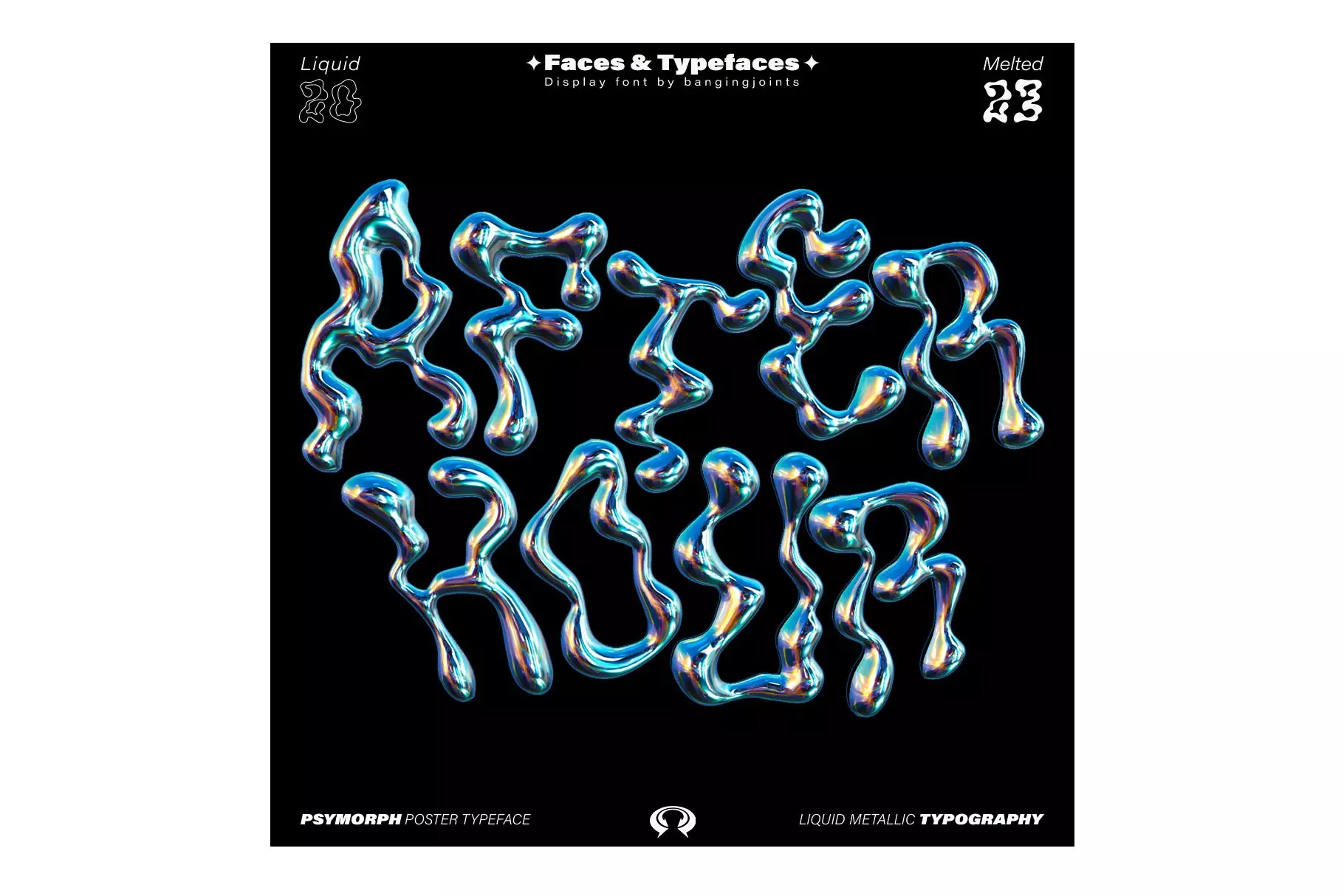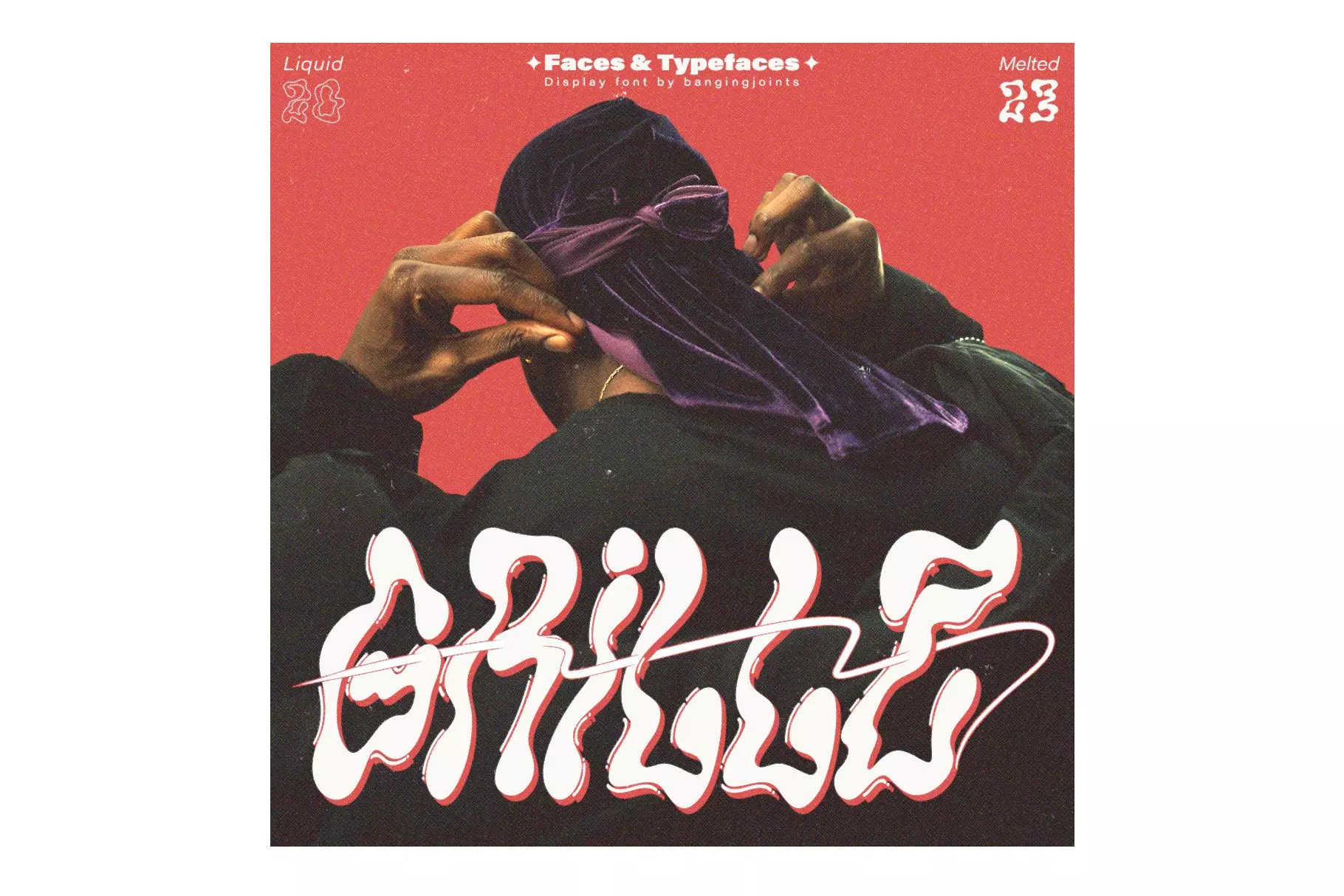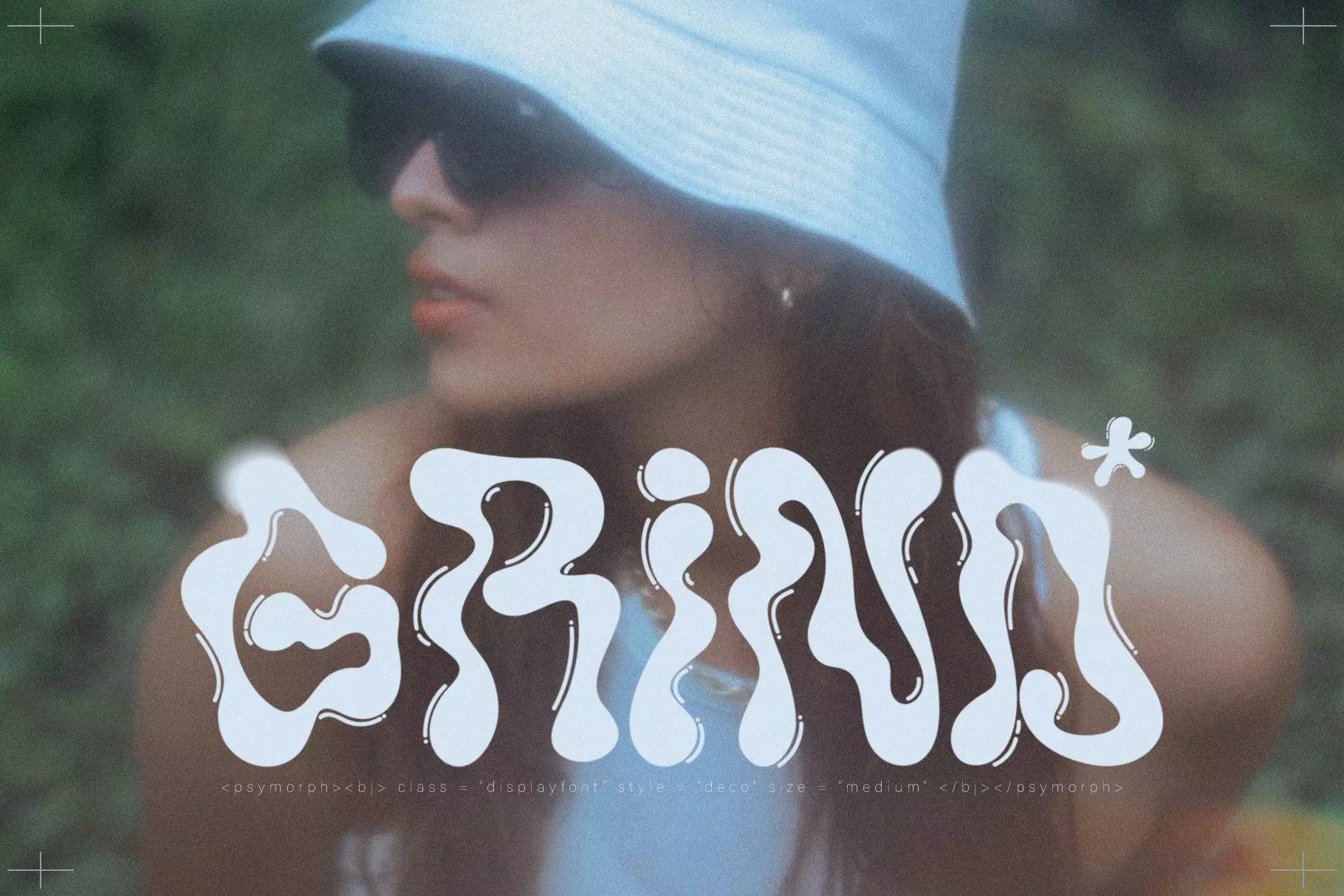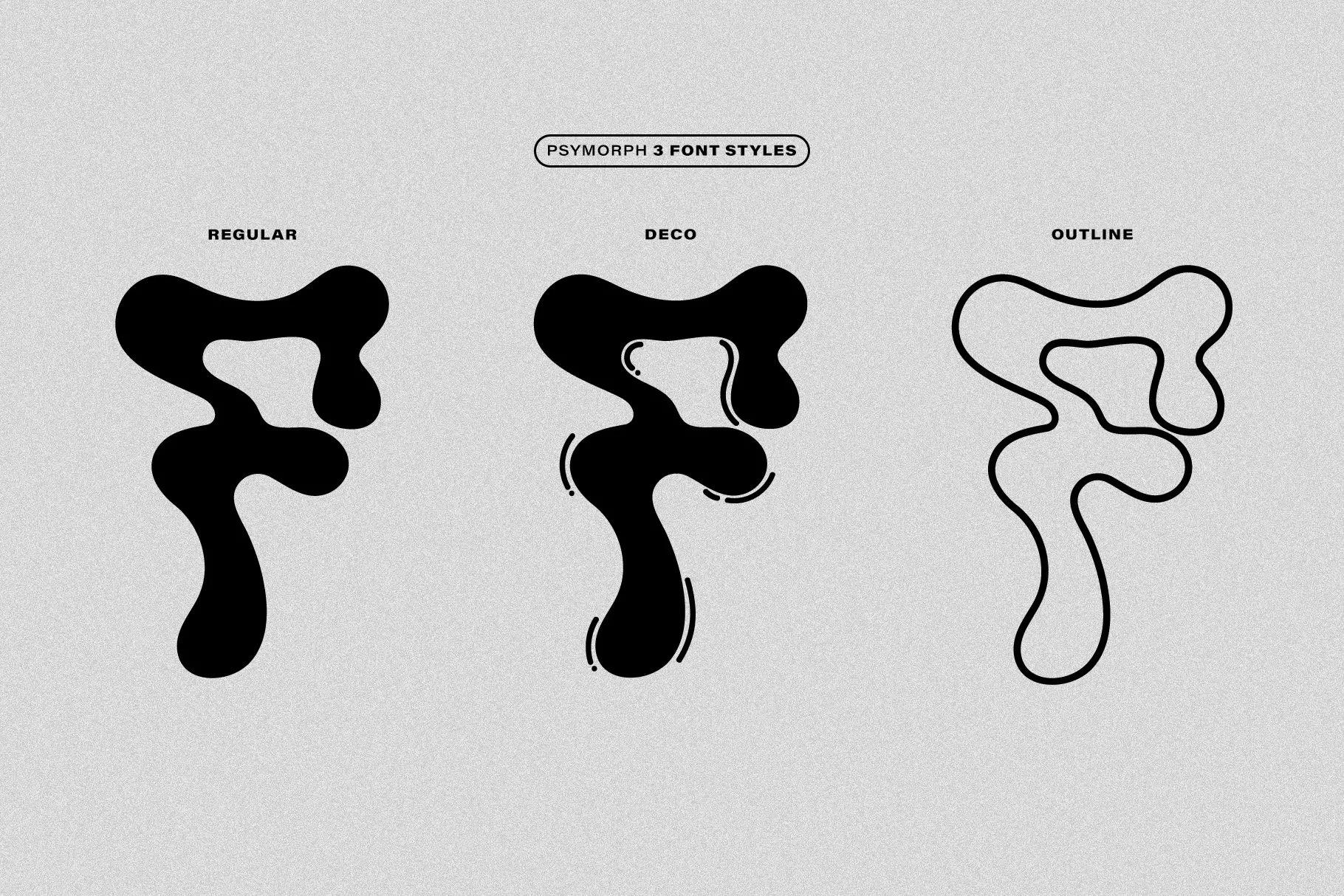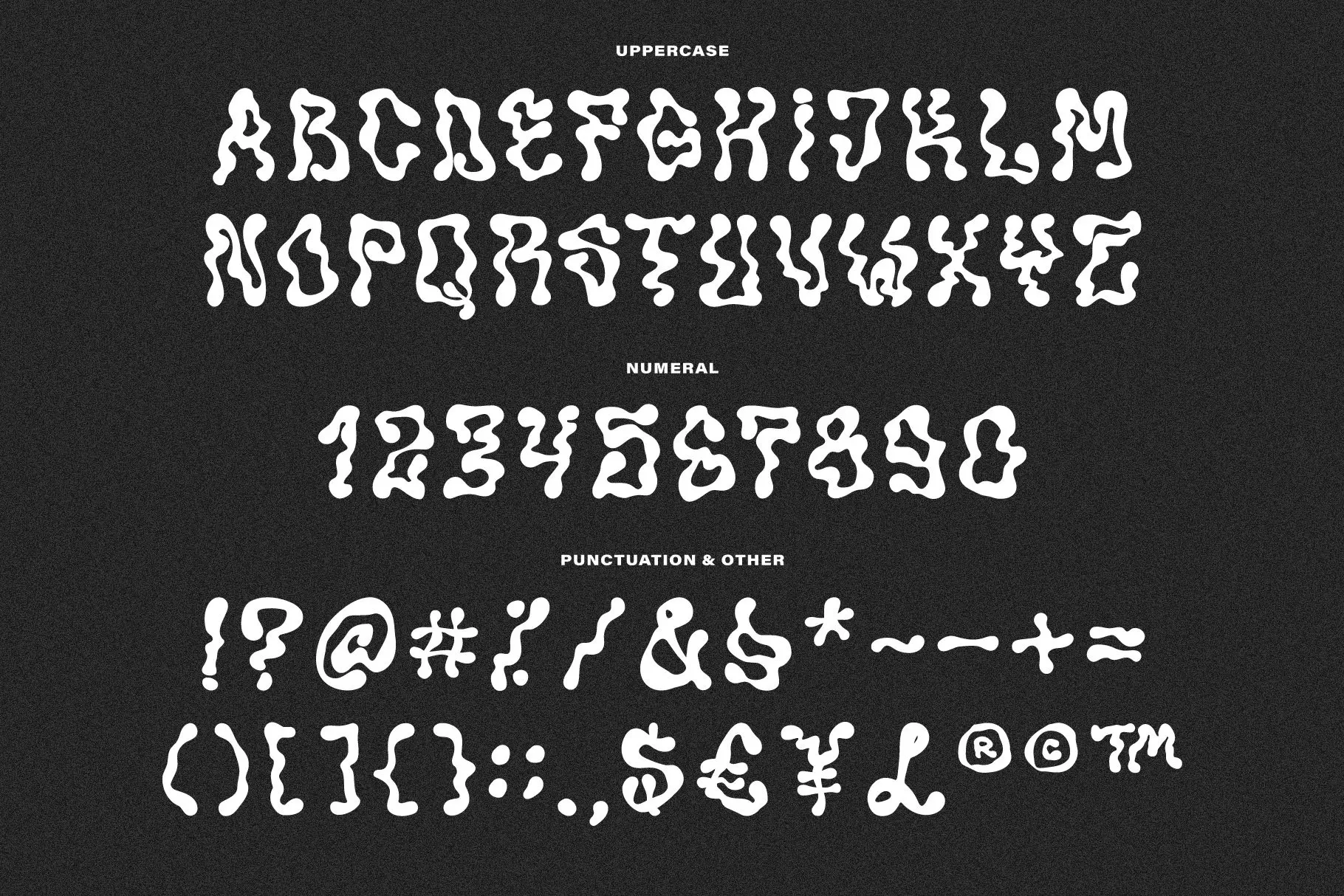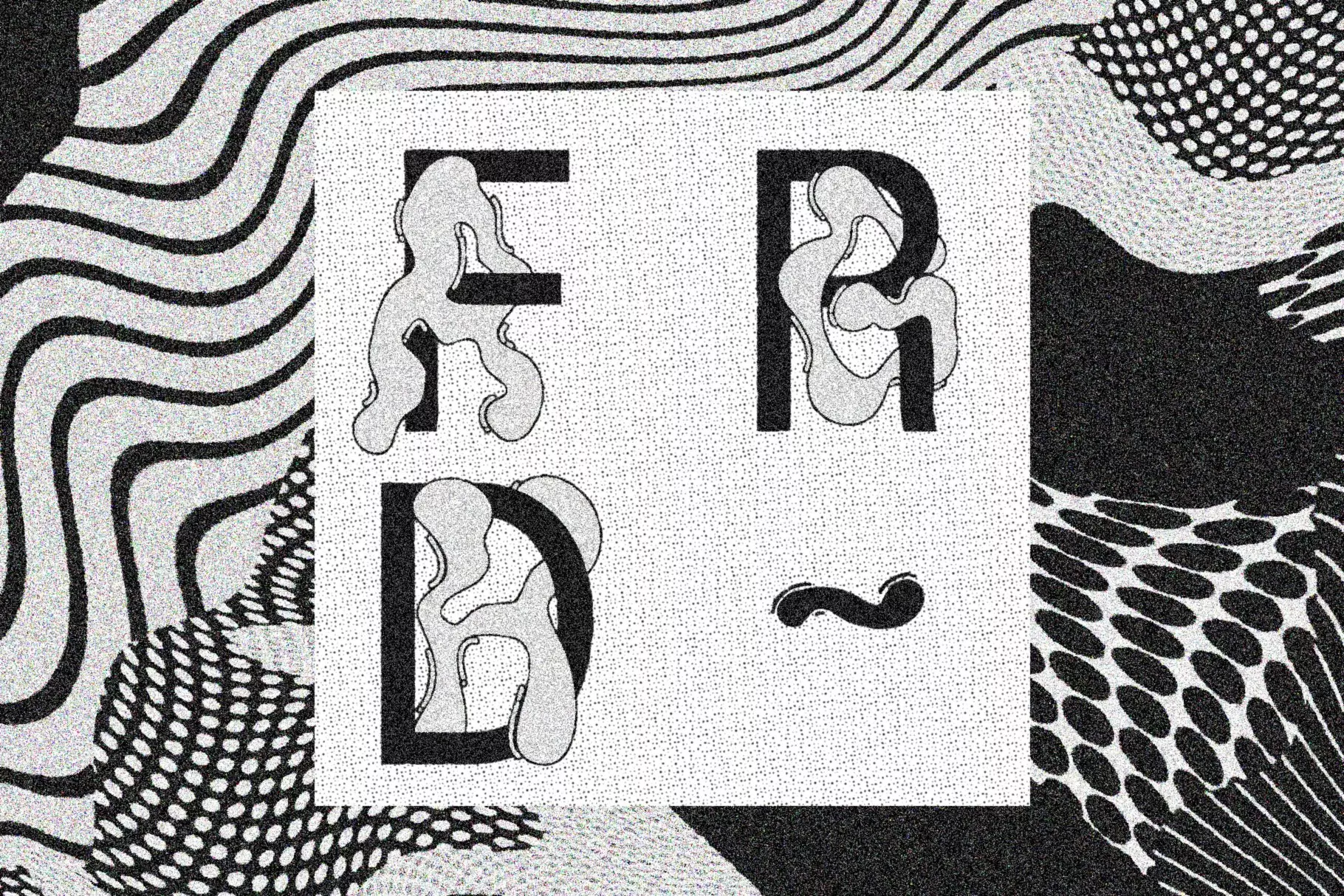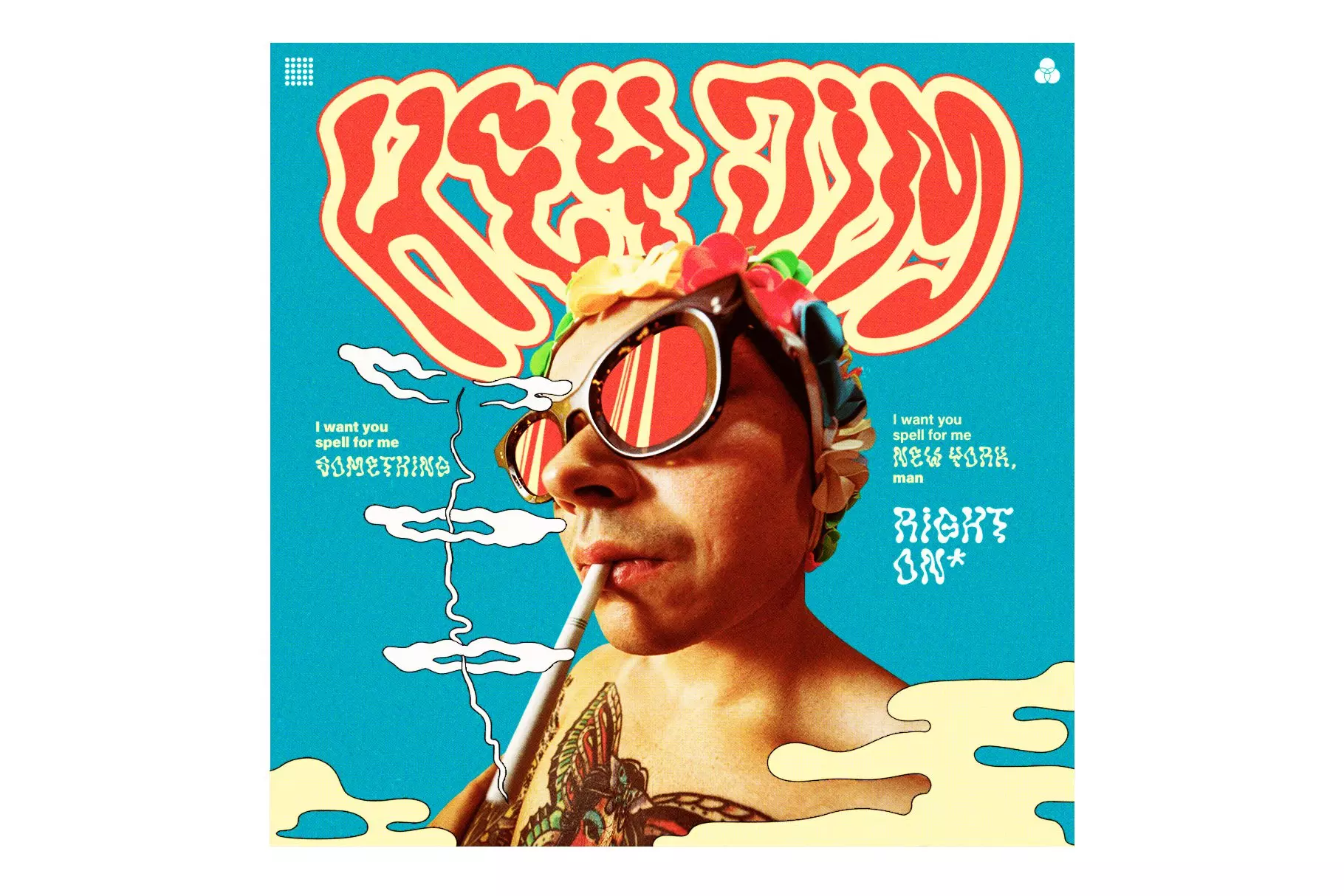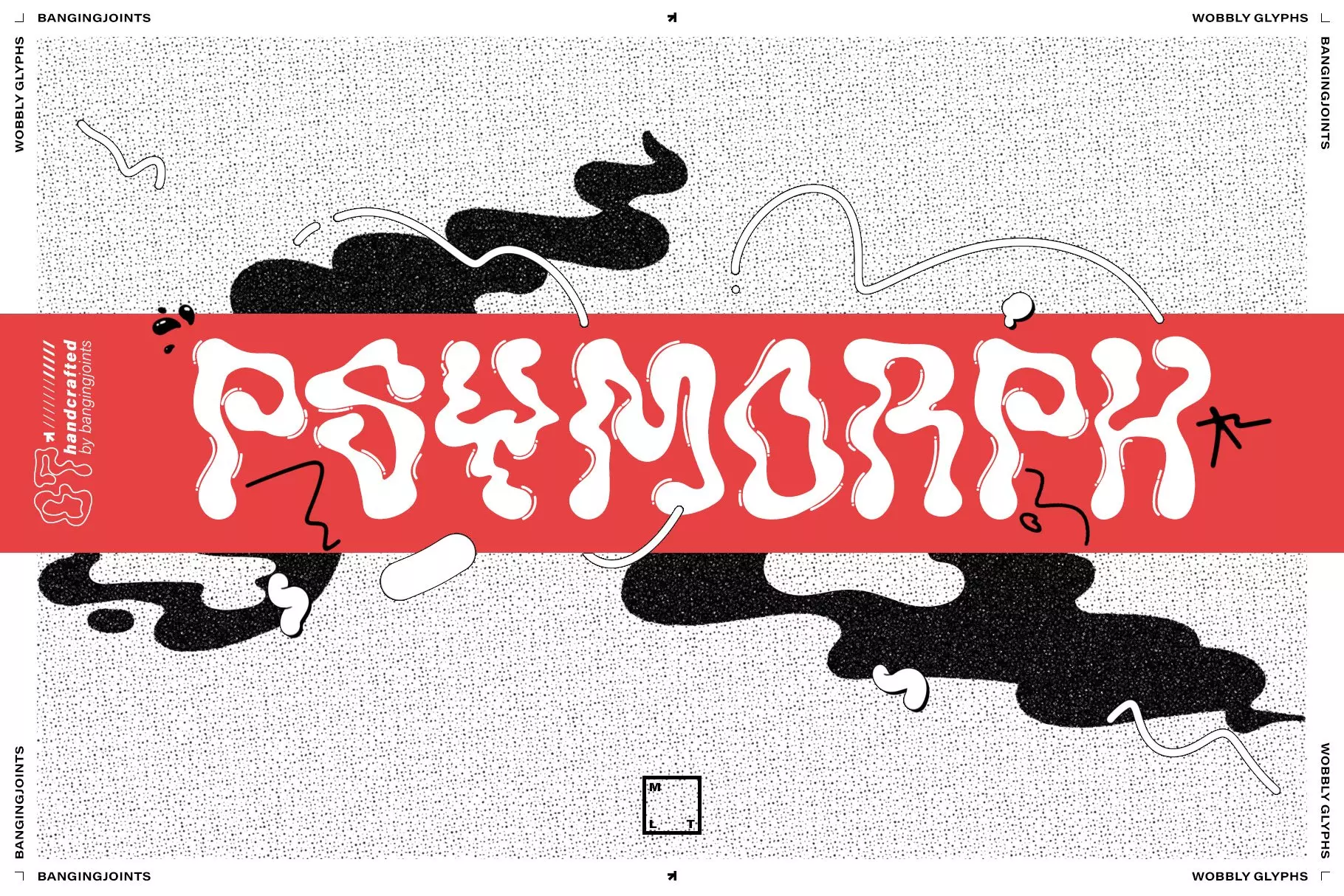
Psymorph là một phông chữ vẽ tay lung linh, vui nhộn, hấp dẫn, ban đầu được lấy cảm hứng từ thẩm mỹ Y2K.
Nó có 3 kiểu, phù hợp cho áp phích, logo, áo phông, tờ rơi, bản in và các tài liệu xây dựng thương hiệu khác.
ĐẶC TRƯNG:
• Chữ hoa
• Số
• Dấu câu
• Có sẵn 3 kiểu